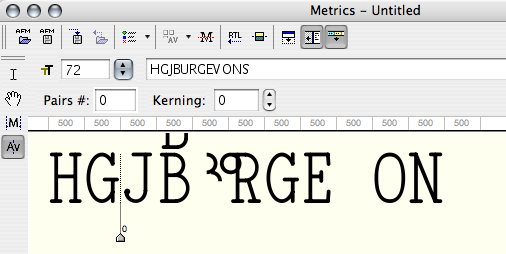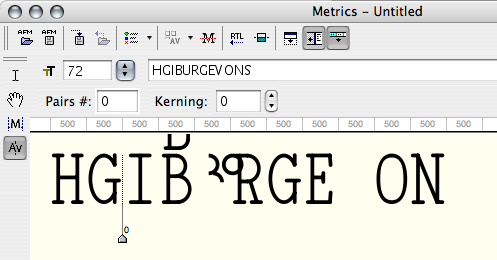
Small Caps in OT?
ich plane einer Schrift Small Caps hinzuzufügen und mich interessiert wie da die gängige Vorgehensweise ist. Macht es Sinn einen seperaten Schriftschnitt zu ergänzen oder lege ich einfach ein OT feature (mir schwebt da „smcp – Small Capitals“ vor) an?
Eigener Schriftschnitt: geht natürlich, ist aber eher veraltet. Vorteile: unkompliziert zu erstellen; Nachteile: Mehrgleisigkeit für alle nicht-betroffenen Zeichen
Opentype: etwas komplizierter, dafür direkt in den Font integriert statt eine "Kopie".
Sollen die Smallcaps in Office-Anwendungen nutzbar sein? --> eigener Schriftschnitt ist die einfachste Lösung, zumindest brauchen die Kapitälchen aber einen Codepoint aus der Private Use Area damit sie in Word & Co ansprechbar sind (Nachteil: Codierung stimmt nicht mit Bedeutung überein, ein Smallcaps-A ist der Tabelle nach kein A oder a, sondern ein Sonderzeichen. Kriegen sie keinen Codepoint zugewiesen, sind sie nur in Opentype-fähigen Programmen erreichbar.
Wenn Opentype: Du brauchst die Features SMCP (Smallcaps) und C2SC (Capitals to Smallcaps). SMCP ersetzt alle Kleinbuchstaben durch Kapitälchen, lässt aber die Versalien stehen. C2SC ersetzt die Versalien durch Kapitälchen, lässt aber die Minuskeln in Ruhe. Indesign verwndet in der Einstellung "Kapitälchen" das SMCP-Feature, in der Einstellung "alles Kapitälchen" die Features SMCP und C2SC kombiniert.
Brauchst du Smallcaps-Satzzeichen wie Rufezeichen, Fragezeichen oder & ? Wie sieht es mit Ziffern aus?
Ich würde auch mehr zu OT tendieren, das blöde ist bloß, daß man einen neuen Kerning-Text hinterlegen muß weil die Zeichen ja nicht mehr "a" sondern k.a. vielleicht "a.Caps" heissen. Oder kann man die OT-Features im Kerning-Dialog (ach so: Fontlab.) aktivieren?
Office-Anwendungen sind nicht das Ziel.
Guter Tipp mit dem "C2SC".
Über Rufezeichen, Fragezeichen, Ziffern etc. hab ich mir ehrlich gesagt noch keine gedanken gemacht. Unter welches feature würden die dann fallen? SMCP oder C2SC oder gar ein anderes?
OT-Features in Fontlab-Metrikfenstern aktivieren: nicht dass ich wüsste (wäre praktisch, aber programmtechnisch nicht ganz einfach bereitzustellen... vielleicht ja in Fontlab 6?).
Aber: Du kannst im Metrikfenster den markierten Buchstaben mit STRG+Mausrad (am Mac eventuell Command+Mausrad?) "weiterblättern", d.h. wenn du A.sc siehst und markiert hast, und dann weiterblätterst, kommst du zu B.sc, ohne das eintippen zu müssen. Wenn du tippen musst, kommt dir zuhilfe, dass du wahrscheinlich den gewünschten Buchstaben schon angezeigt bekommst, wenn du nur "A." eingetippt hast (vorausgesetzt du hast noch nicht weitere Varianten eingebaut, wie, "A.ti", "A.sw" usw.). Ich bin inzwischen beim Kerning von Smallcaps praktisch gleich schnell wie bei "normalen" Alphabeten, getippt wird eigentlich gar nicht mehr, ich habe meine "Kontext-Zeichen" außen, und die betroffene Kombination wird nur noch per Mausrad weitergeblättert (wenn jetzt noch jemand einen Tipp hat wie ich statt der Maus eine Tastaturtaste dafür verwenden kann: her damit, dann bin ich noch schneller).
Die Smallcaps solltest du "A.sc" nennen, das ist offenbar gängige Praxis und kurz genug zum schnellen Tippen falls notwendig.
Rufezeichen, Fragezeichen, ... Ist sicher ein Streitpunkt, in welches Feature das gehört. Nachdem im gemischten Satz Versalien sowieso aus dem Textband hervorstehen, speziell natürlich im Deutschen, können das auch Fragezeichen und Rufezeichen tun. Somit würde ich die eher ins C2SC-Feature packen. Gut möglich dass ich das nächste Woche wieder ganz anders sehe ;-)
Hast du spezielle Kapitälchenziffern, können ggf. auch Kapitälchen-Währungszeichen notwendig werden, nimmst du hingegen die Minuskelziffern für Kapitälchen, können meiner Meinung nach auch die normal-hohen stehenbleiben.
Aber: übertreib's nicht mit diesen Sonderzeichen, im Kapitälchensatz sind diese Dinge dermaßen selten, dass man sich echt fragen muss ob der Aufwand und die zusätzliche Komplexität lohnt – hängt von der Schrift und deren Einsatzzweck ab.
Ist aber mal ein Muss für die Version 6. Obwohl ich mir in diversen Apps seit Jahren ungehört simple Features wünsche... ;)
Ich bin ehrlich gesagt kein Freund von Paar-Kerning sondern habe lieber einen Satz bzw. ein Wort drumrum. Muß vielleicht mal an meinen Kerning Text mit Suchen/Ersetzen ran.
Oh, du kannst im Metrix- so wie im Glyph-Fenster mit "," und "." vor und zurück navigieren. Die Mouserad-Varinate war mir neu aber ich benutze relativ selten die Mouse und versuche das gern über Tastenkürzel zu erschlagen.
Habs automatisch "a.SC" genannt, vielleicht sollte ich nochmal die Groß-/Kleinschreibung überdenken. ;)
Oh ja ich hab schon gemerkt, daß die Sonderzeichen "ä", "á" etc. schon einen ziemlichen Rattenschwanz nach sich ziehen. :/ Der Aufwand lohnt sich wahrscheinlich nicht, aber es wär halt ganz cool, wenn man mal weiß wie’s funktioniert, und es trotzdem implementiert, auch wenns dann niemand nutzt.
Wieder was gelernt. :) Thnx for Support.
Paarkerning: ich mach es meistens mit solchen Testketten:
minimumaaminomon
minimumabminomon
minimumacminomon
D.h. ich schaue dass ich über die Metrik ein perfektes Bild für "einfache" gerade Zeichenkombinationen hinkriege (minimum), kerne dann ggf. noch die Kombination von runden und geraden Zeichen (nnnonnnnoonnnnn) falls nötig, und nehme das dann als Umgebung und Vergleichsmöglichkeit für alle anderen Kombinationen, die ich in die Mitte stelle (aa, ab, ac, ad ...) und durchackere. Ich hab's auch aufgegeben lange zu überlegen welche Kombinationen denn nun "gebraucht" werden und welche nicht, ich stoße bei fremdsprachigen Testtexten immer wieder auf Kombinationen von denen ich dachte dass die niemals vorkommen, insofern kerne ich inzwischen innerhalb eines Alphabets praktisch "alles mit allem" - ein Lucas-de-Groot'scher Rundumschlag praktisch.
Und genau deswegen habe ich die Frage in den Raum geworfen, ob die IPA-Bereiche dann nicht das kleinere Übel wären. Statt zufälliger Zeichen/Ornamente/Logos sähe man dann eben die »kapitälchenförmigen« small capital letters – und könnte das Geschriebene also wenigstens noch entziffern.
Dass es generell Murks ist, Kapitälchen über Unicode statt Opentype anzusprechen, ist hier wohl unstrittig. Es geht mir nur darum, welche Notlösung weniger Probleme aufwirft.